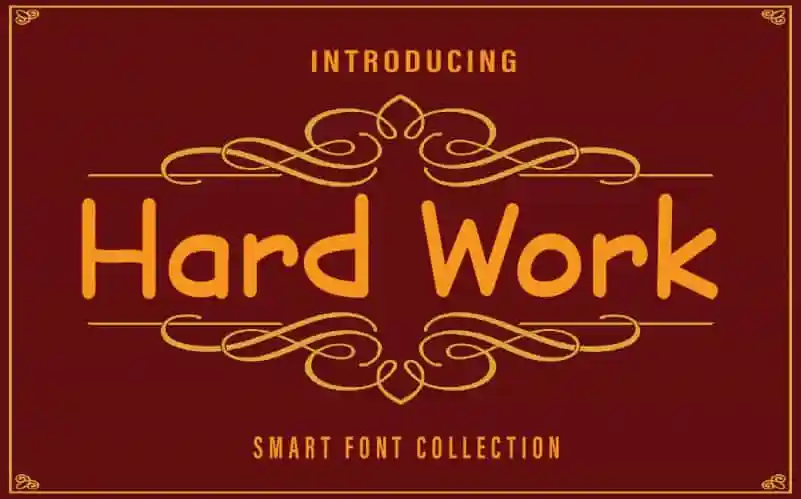
Hard Work Display Font – Fonte Grátis
Hard Work Display Font
A Hard Work Display Font é uma fonte que combina a simplicidade com uma escrita autêntica e única, perfeita para quem busca criar design minimalista com um toque de personalidade. Esta fonte pode facilmente se alinhar à uma infinidade de projetos, permitindo-lhe agregar sua criatividade ao seu trabalho sem comprometer a legibilidade. Experimentar esta fonte pode transformar seus ideais em algo ainda mais notável e único, ajudando-o a destacar sua visão para cada projeto. Com um visual despojado e moderno, Hard Work Display é uma escolha perfeita para quem busca estilizar seu trabalho de forma simples, mas eficaz. A fonte da Farz Studio oferece uma versatilidade que permite usá-la em uma grande variedade de ambientes, garantindo que você tenha sempre um estilo único à mão.